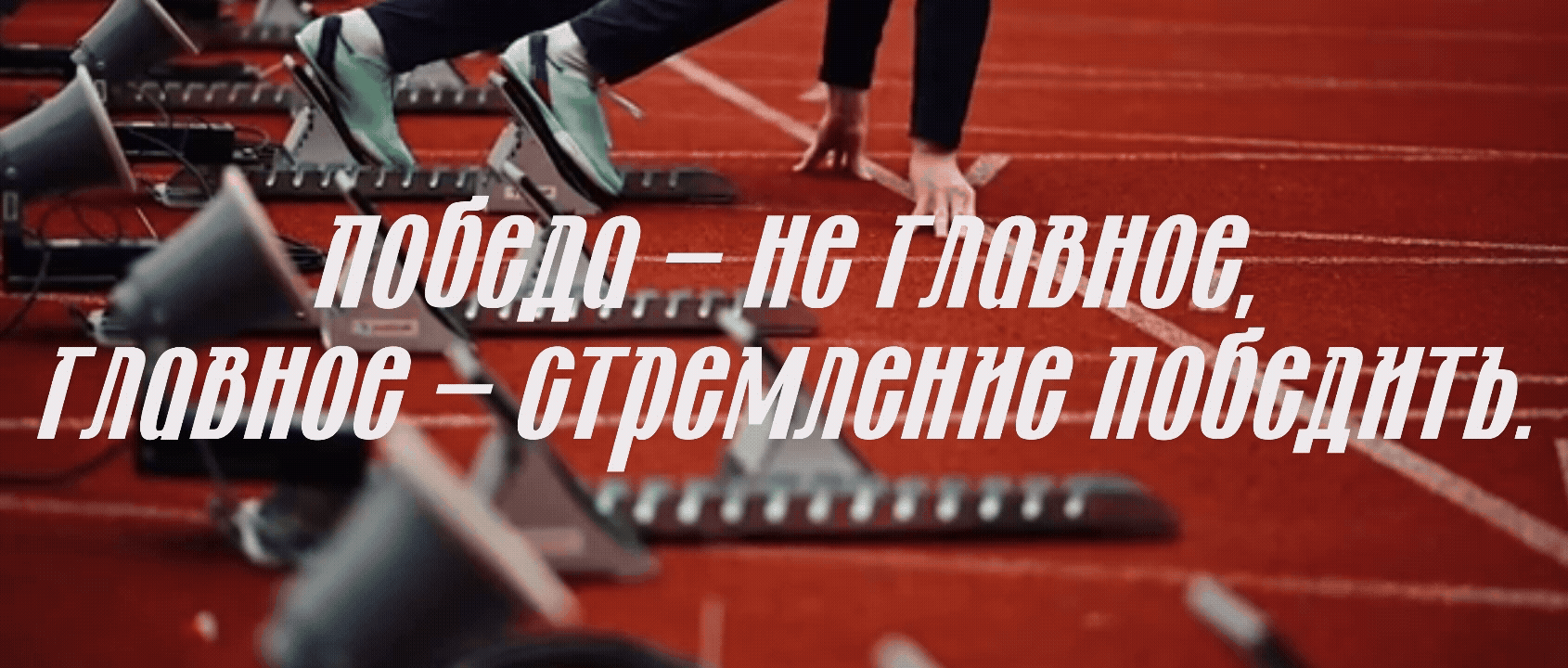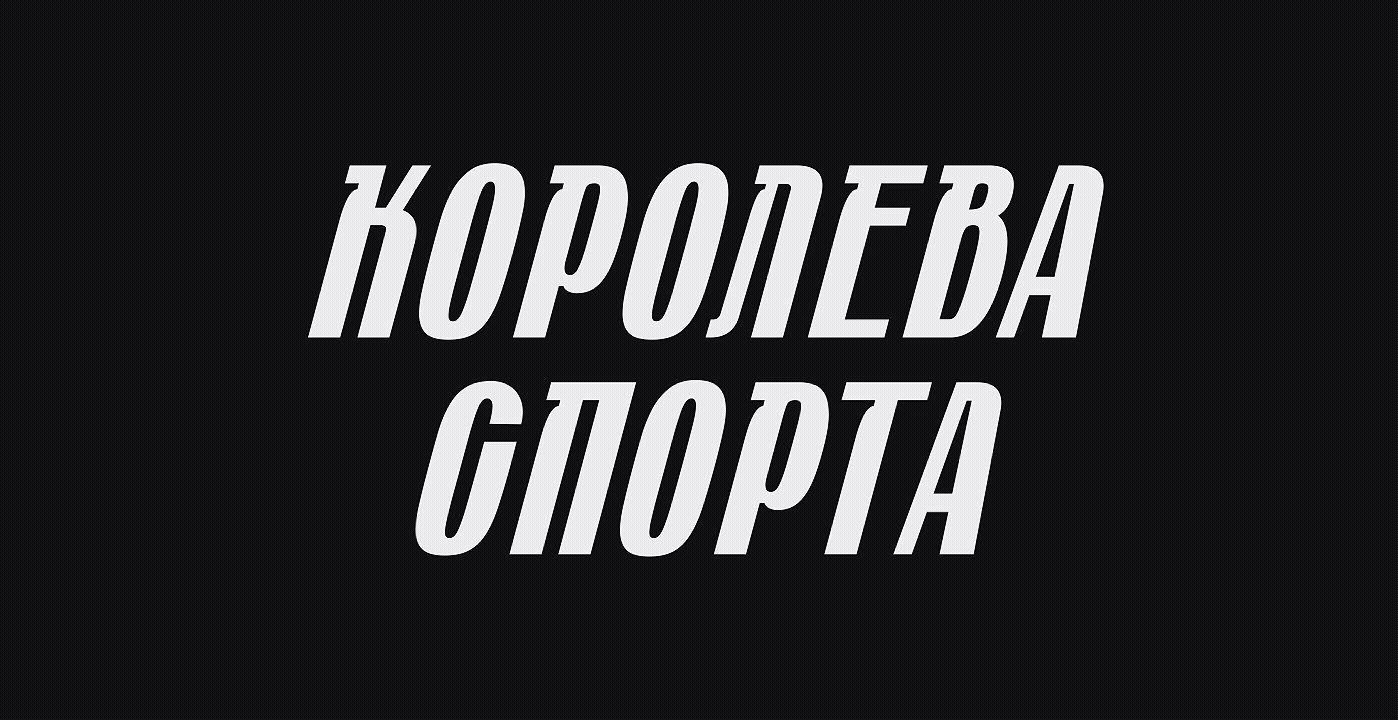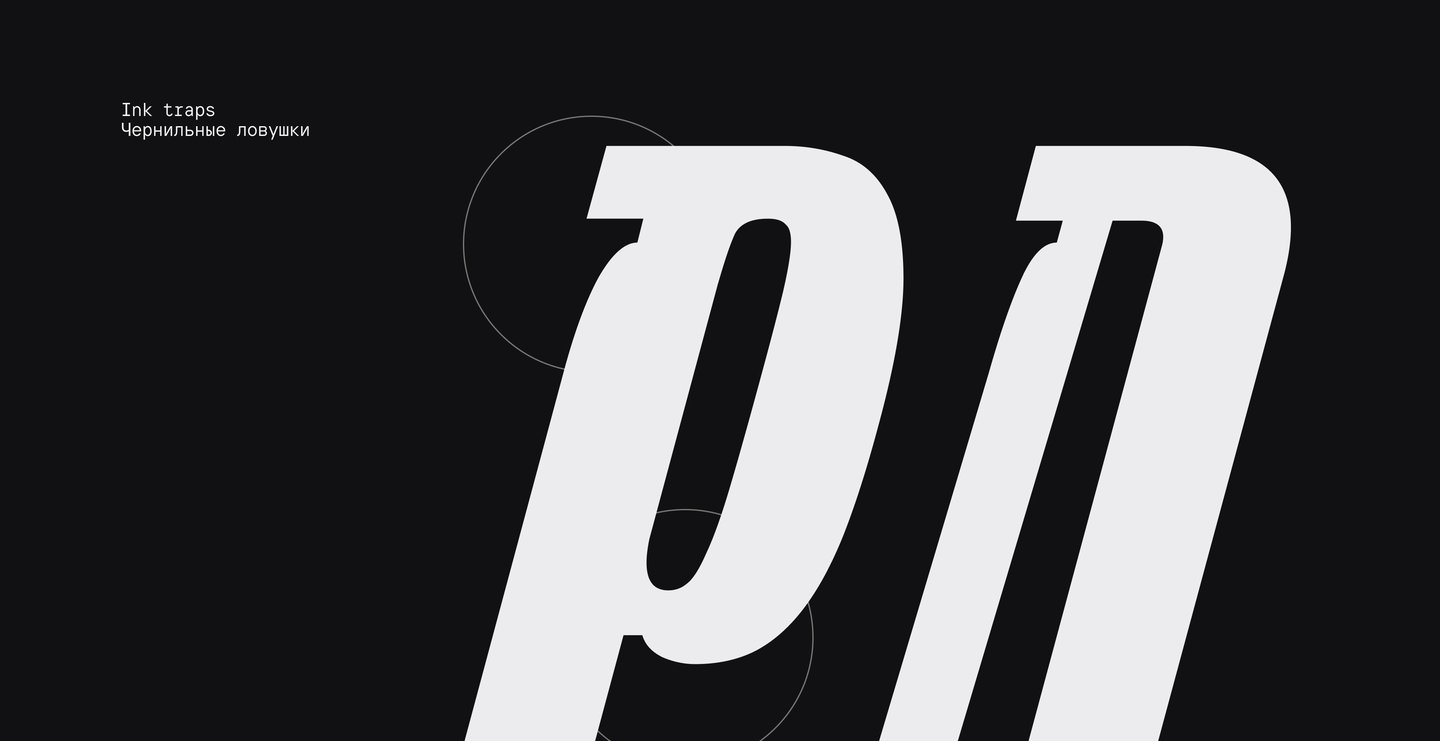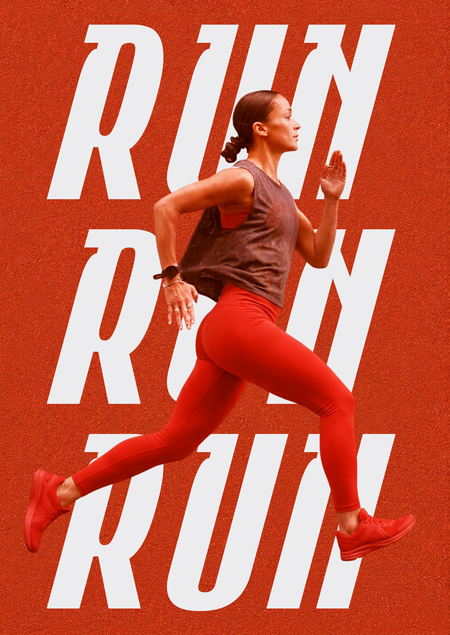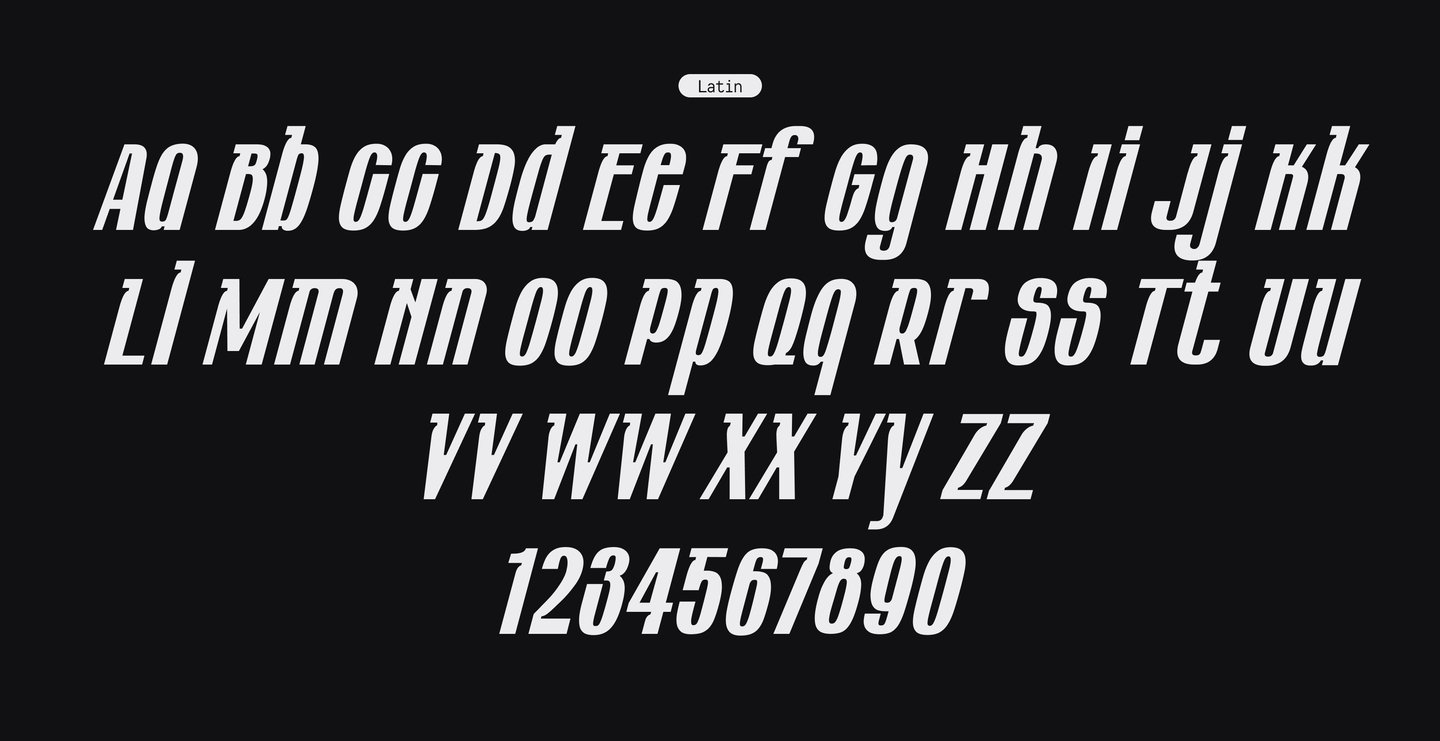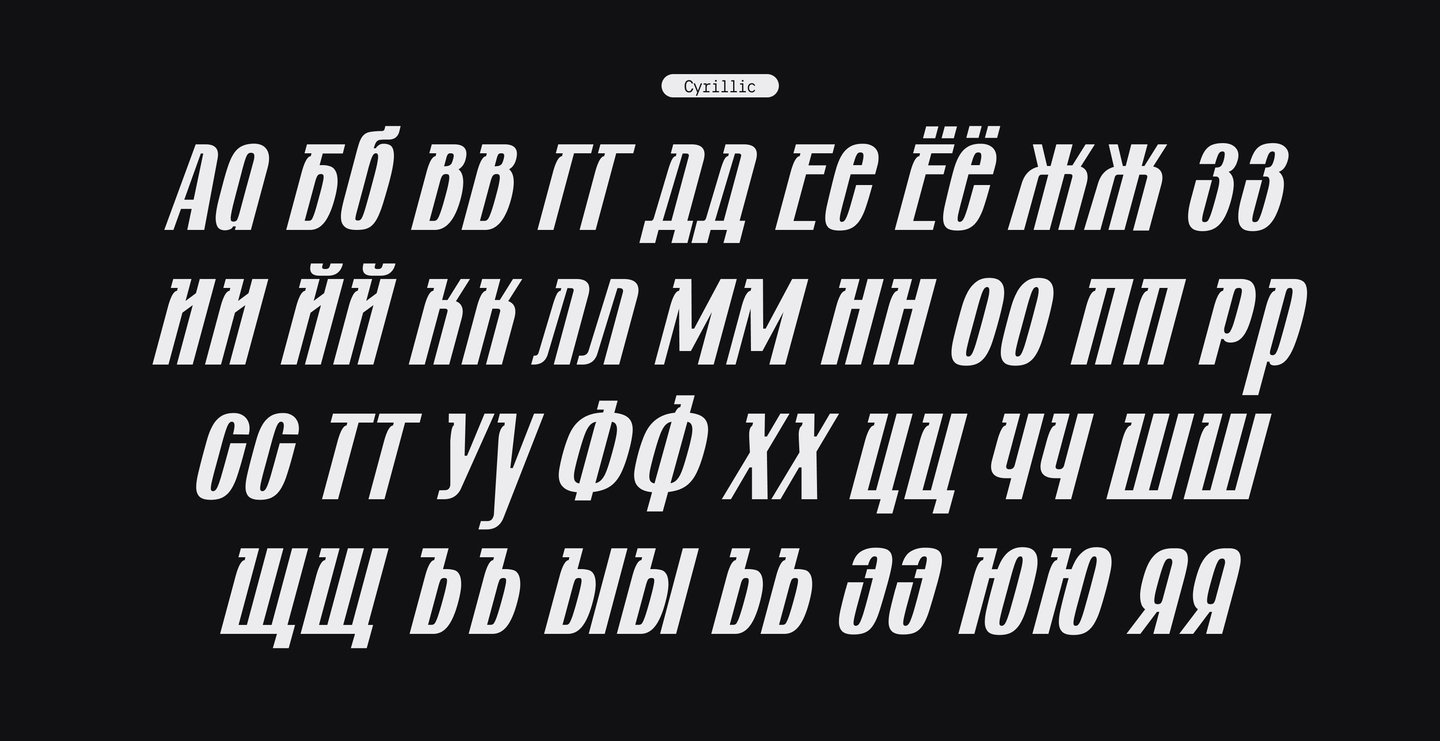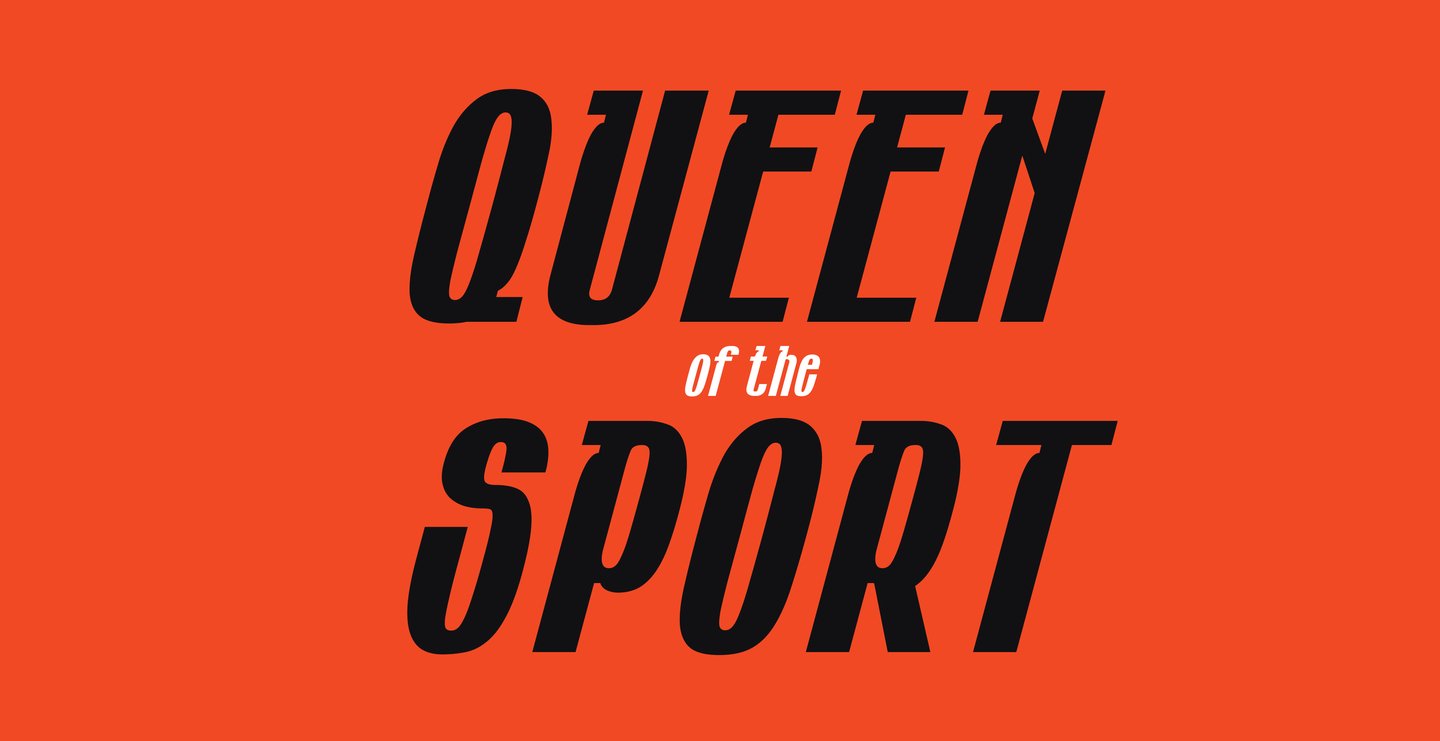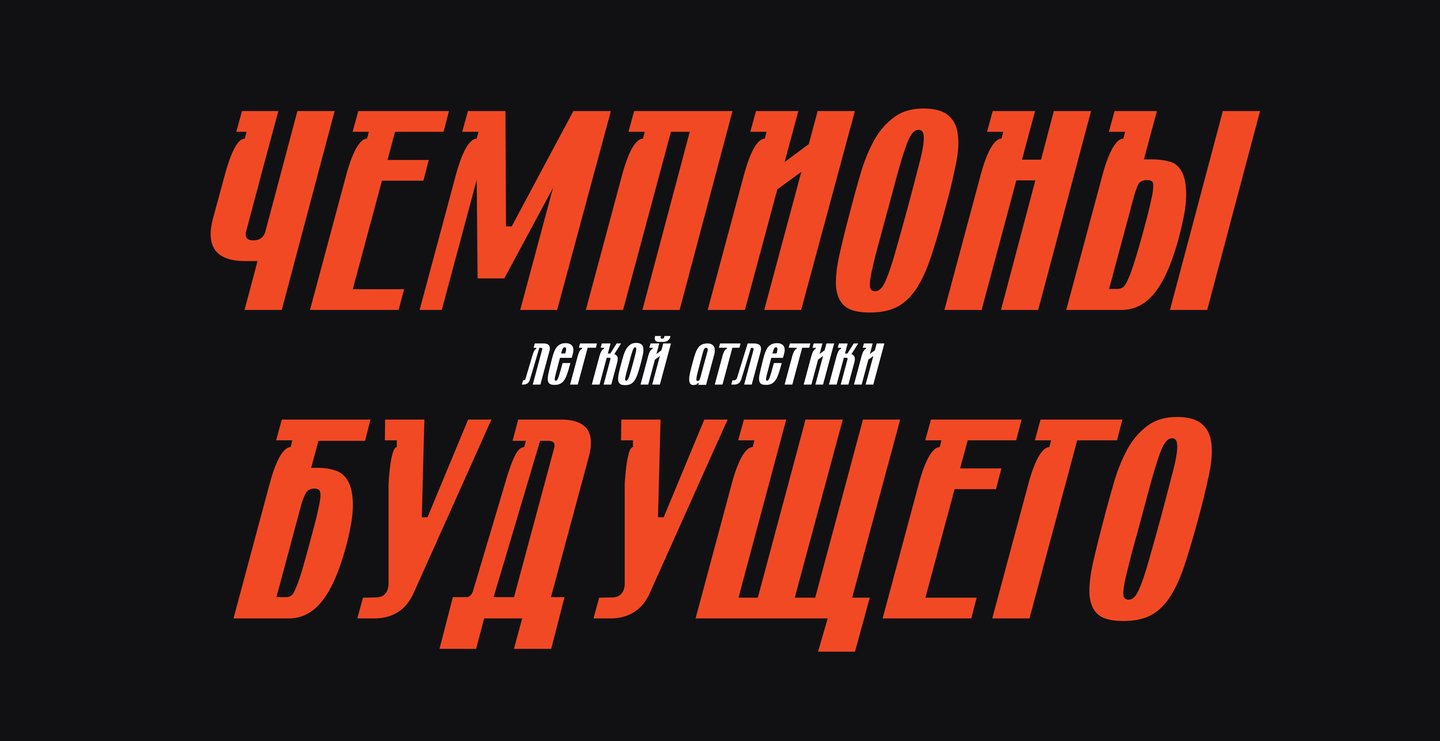
Athla — это акцидентный уникейсный гротеск под небольшим наклоном и со спортивным характером, специально разработанный для российского сериала про легкую атлетику «Королева спорта». Шрифт отлично подходит для заголовков и крупного набора.
При создании шрифта я вдохновлялась формой классического круглого свистка, который традиционно используют тренеры. Эта деталь отражает идею того, что «все в руках не только спортсмена, но и тренера». Кроме того, наклон букв передаёт ощущение напряжения и ожидания, характерное для спортивных соревнований в момент перед стартовым свистком.
Кириллица и латиница